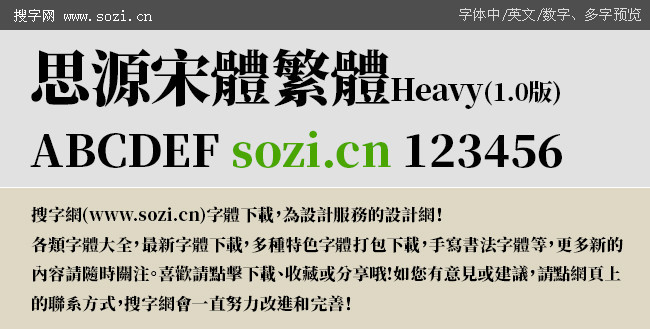
思源宋體繁體Heavy
搜字網(wǎng)提供一款思源宋體繁體Heavy中文字體下載,思源宋體是一款由谷歌聯(lián)合Adobe發(fā)布全新開源字體,是一款免費、開源宋體字體。有 65535 個字形,可共同呈現(xiàn)一致的視覺美感。Heavy是一款比較粗的字重,本作品適用于書籍設(shè)計、畫冊設(shè)計,網(wǎng)頁設(shè)計及包裝設(shè)計等廣告設(shè)計應(yīng)用。